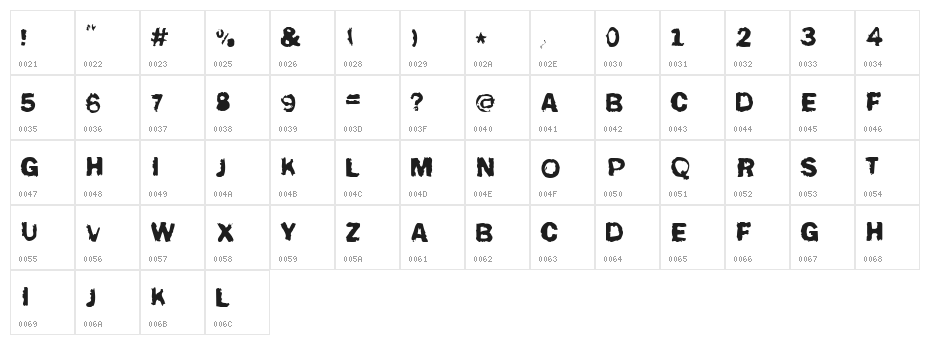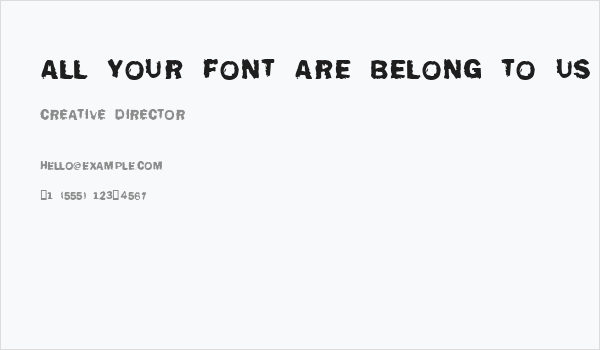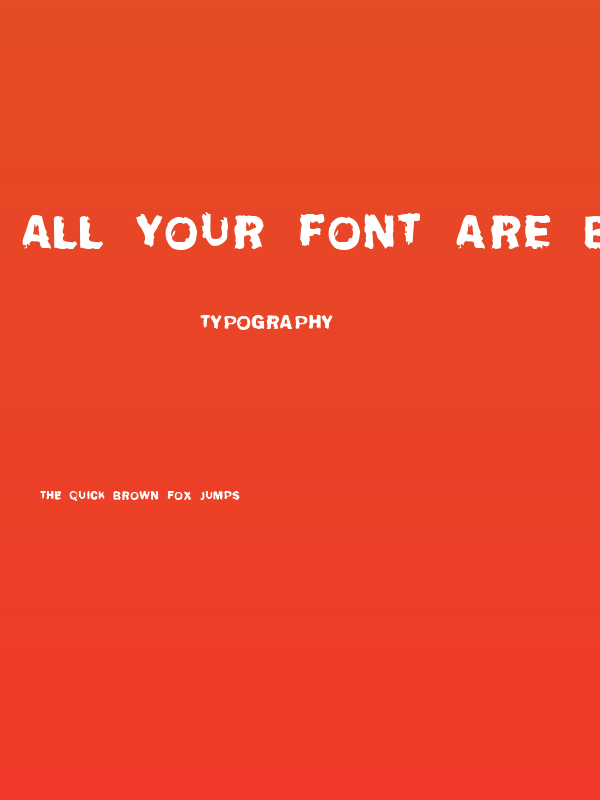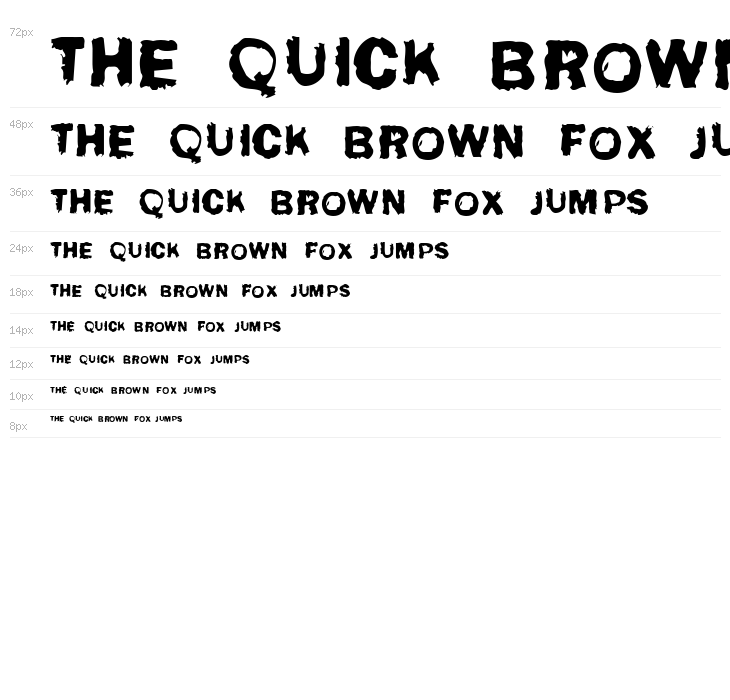
All your font are belong to us Font
| Stile generale | Grunge, Edgy |
| Progetti proposti | Ideal for album covers, posters, urban-themed designs, and any project needing a gritty, bold statement. |